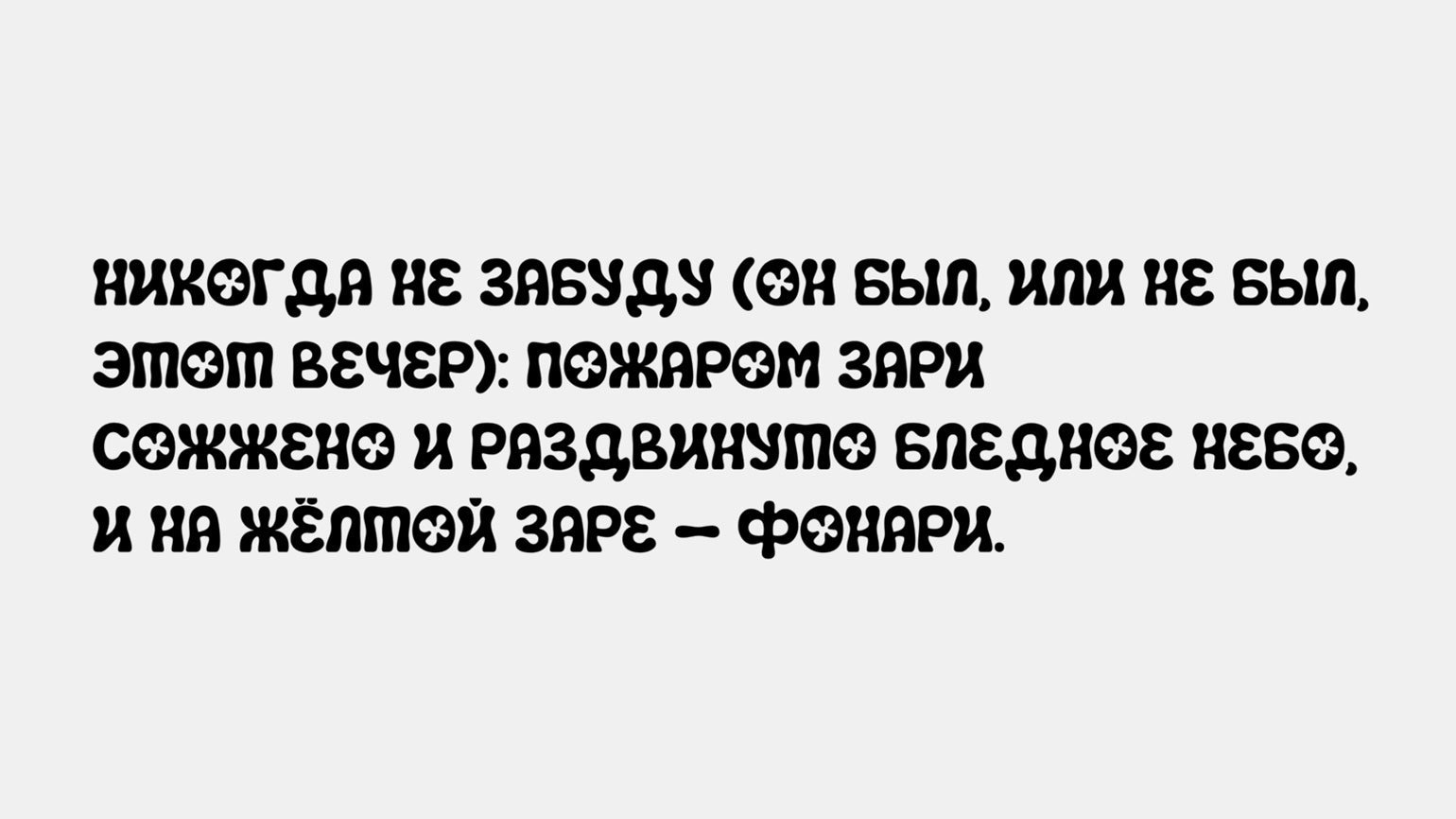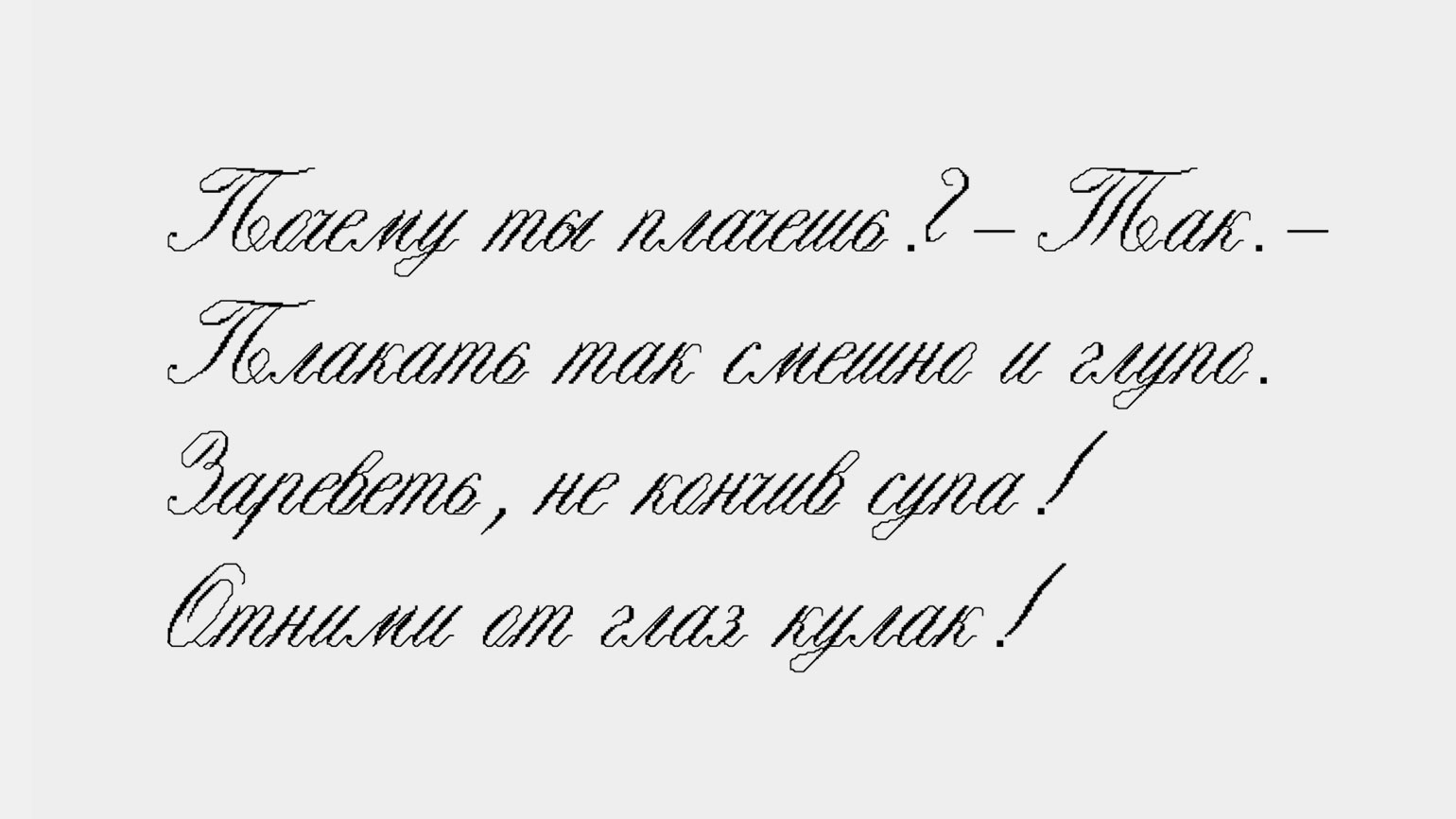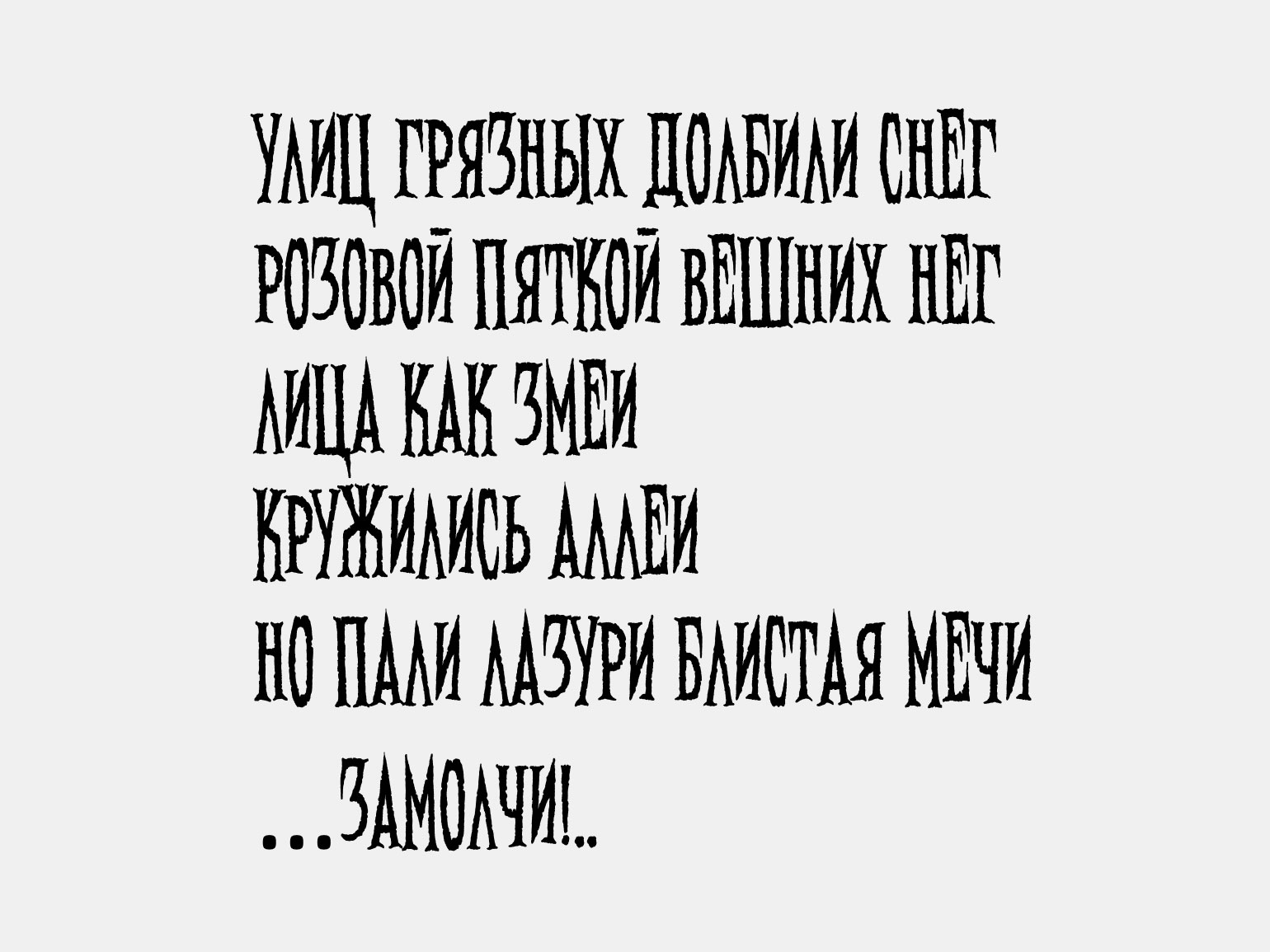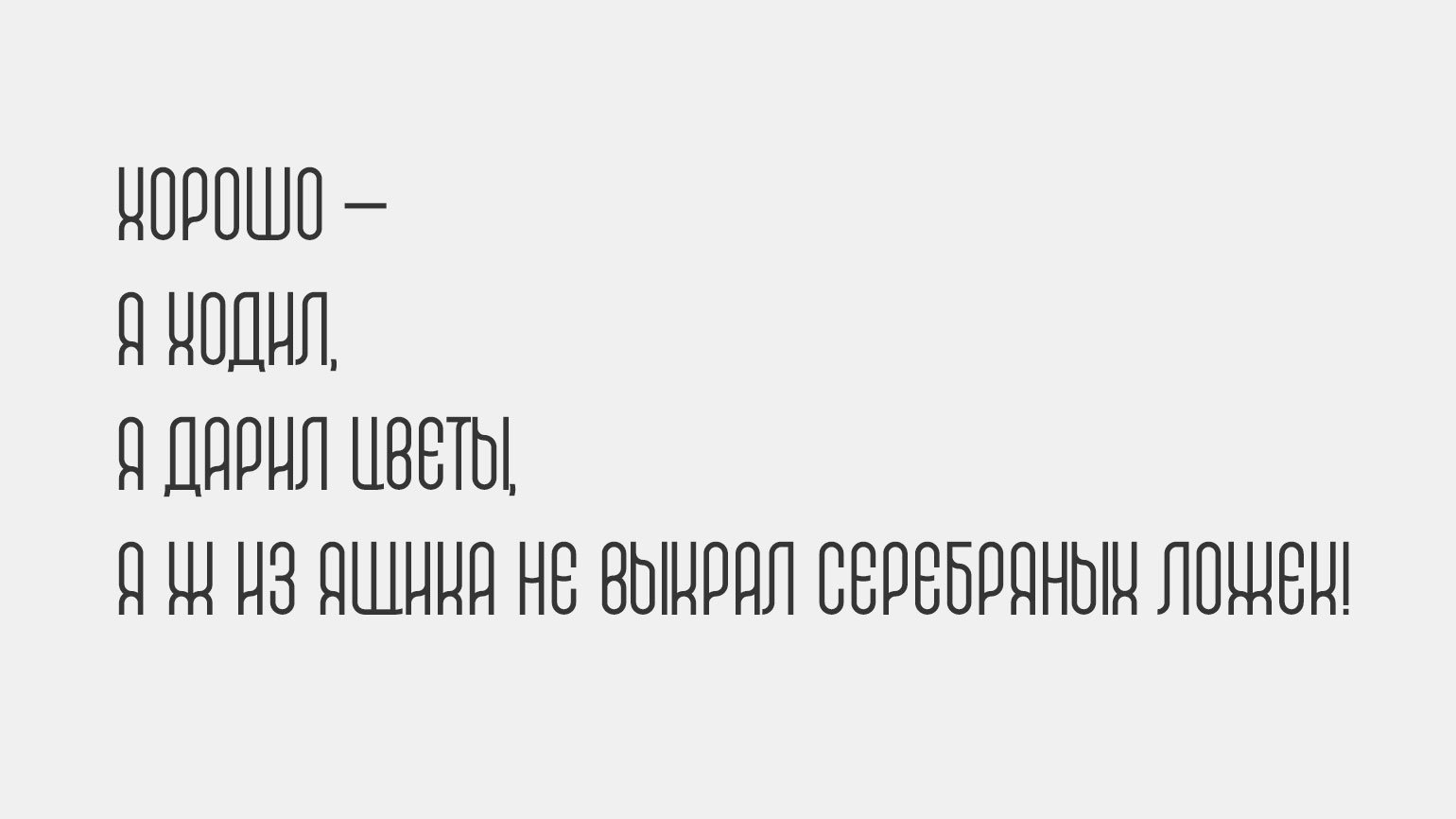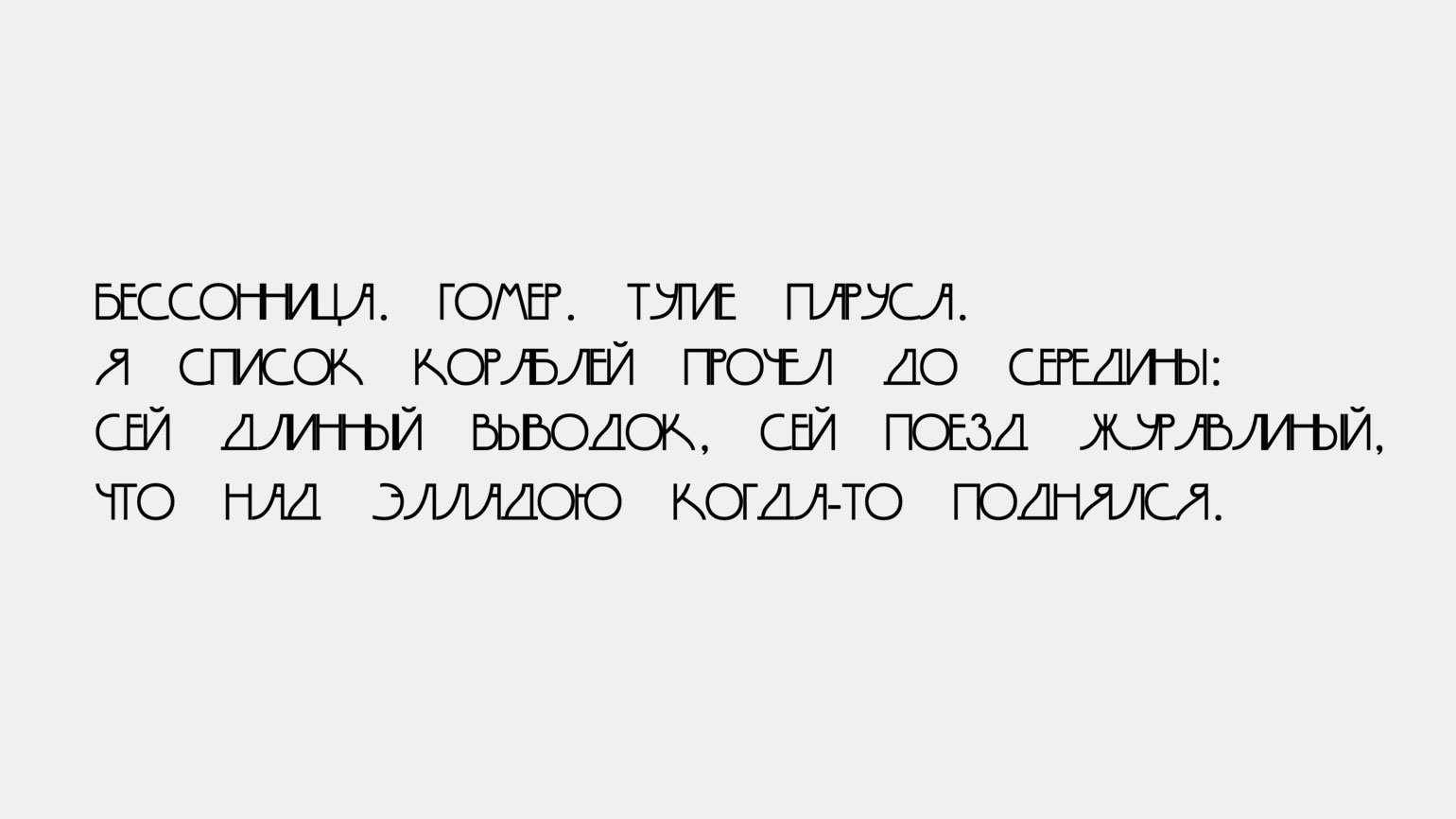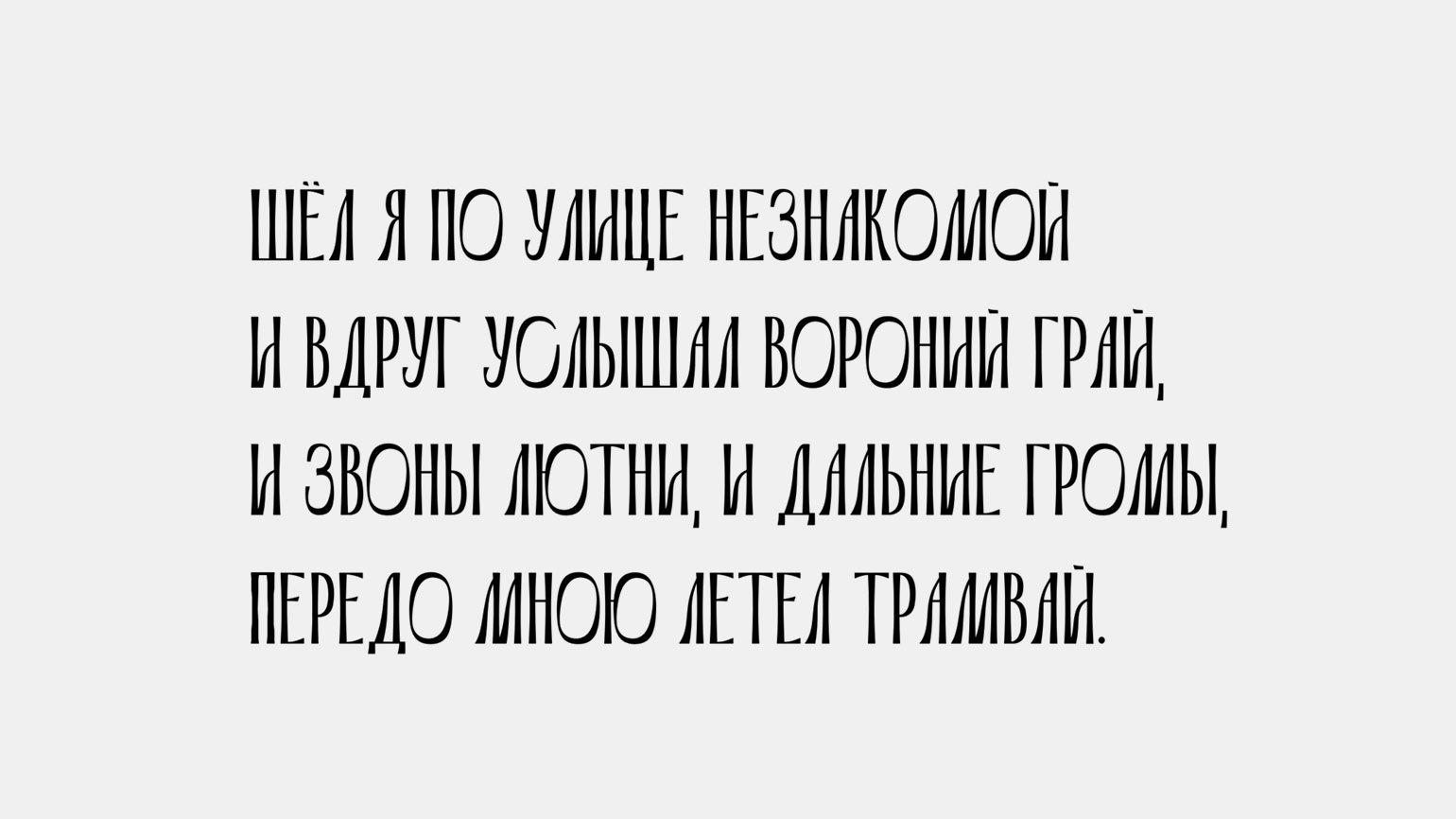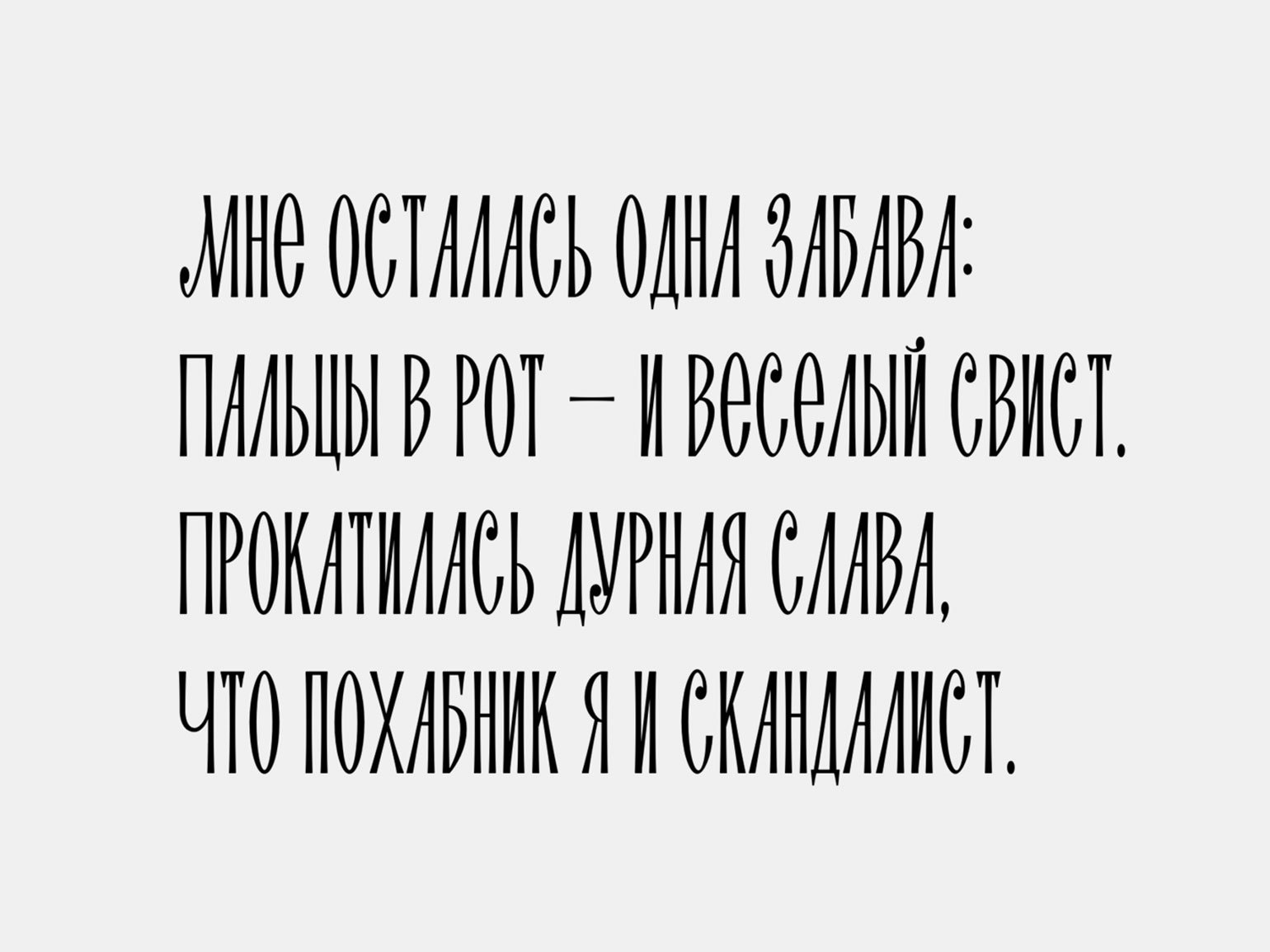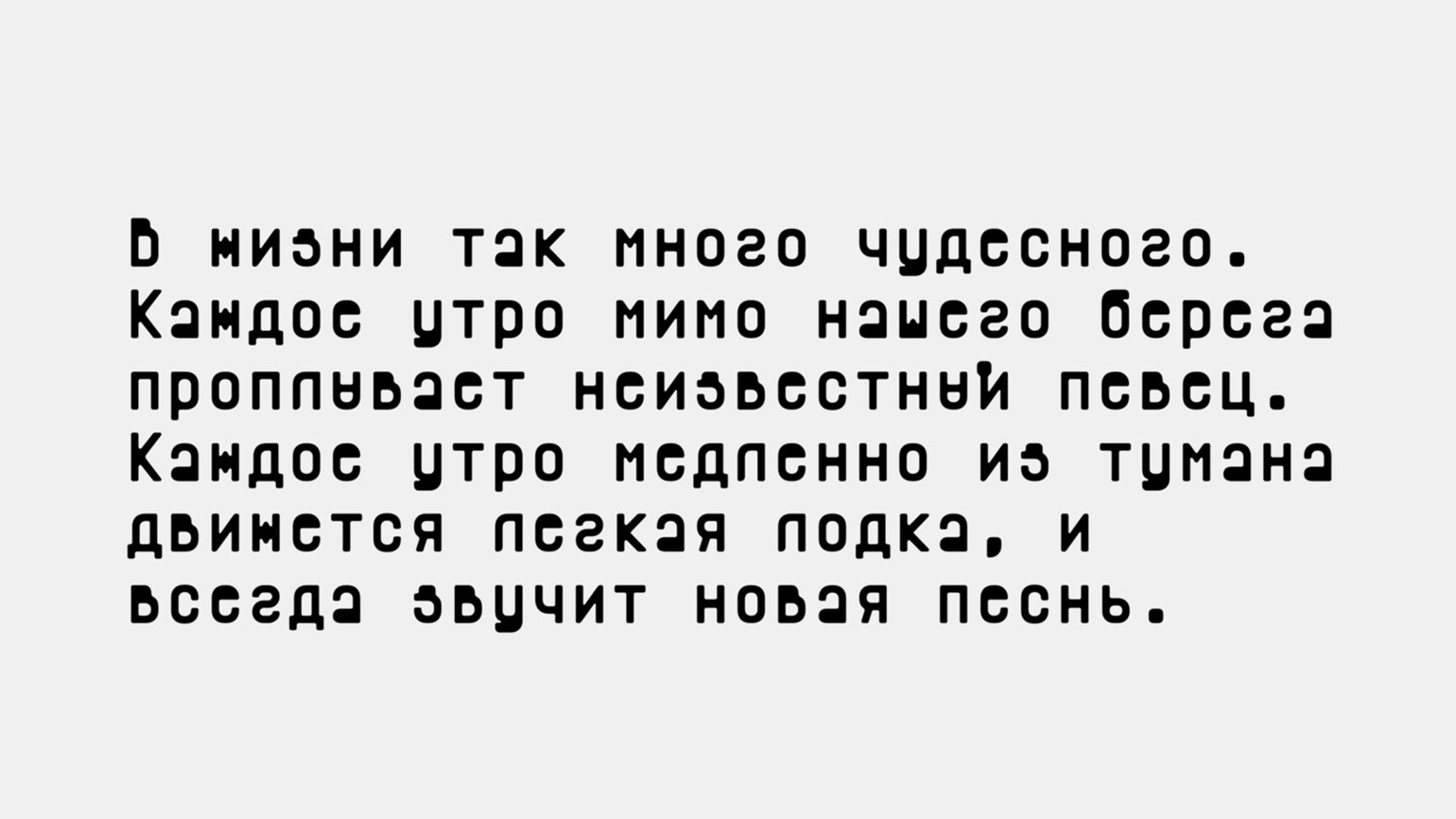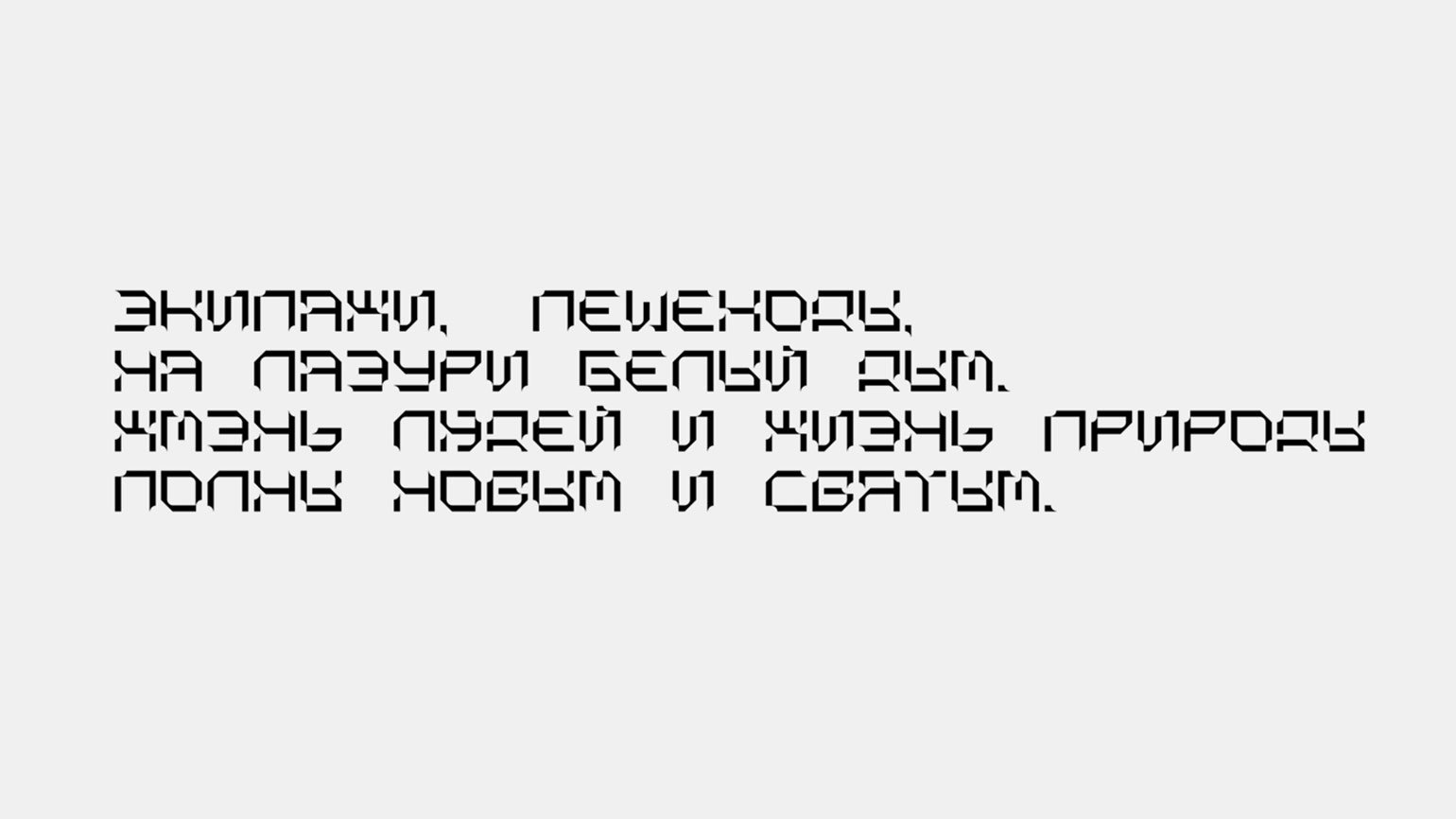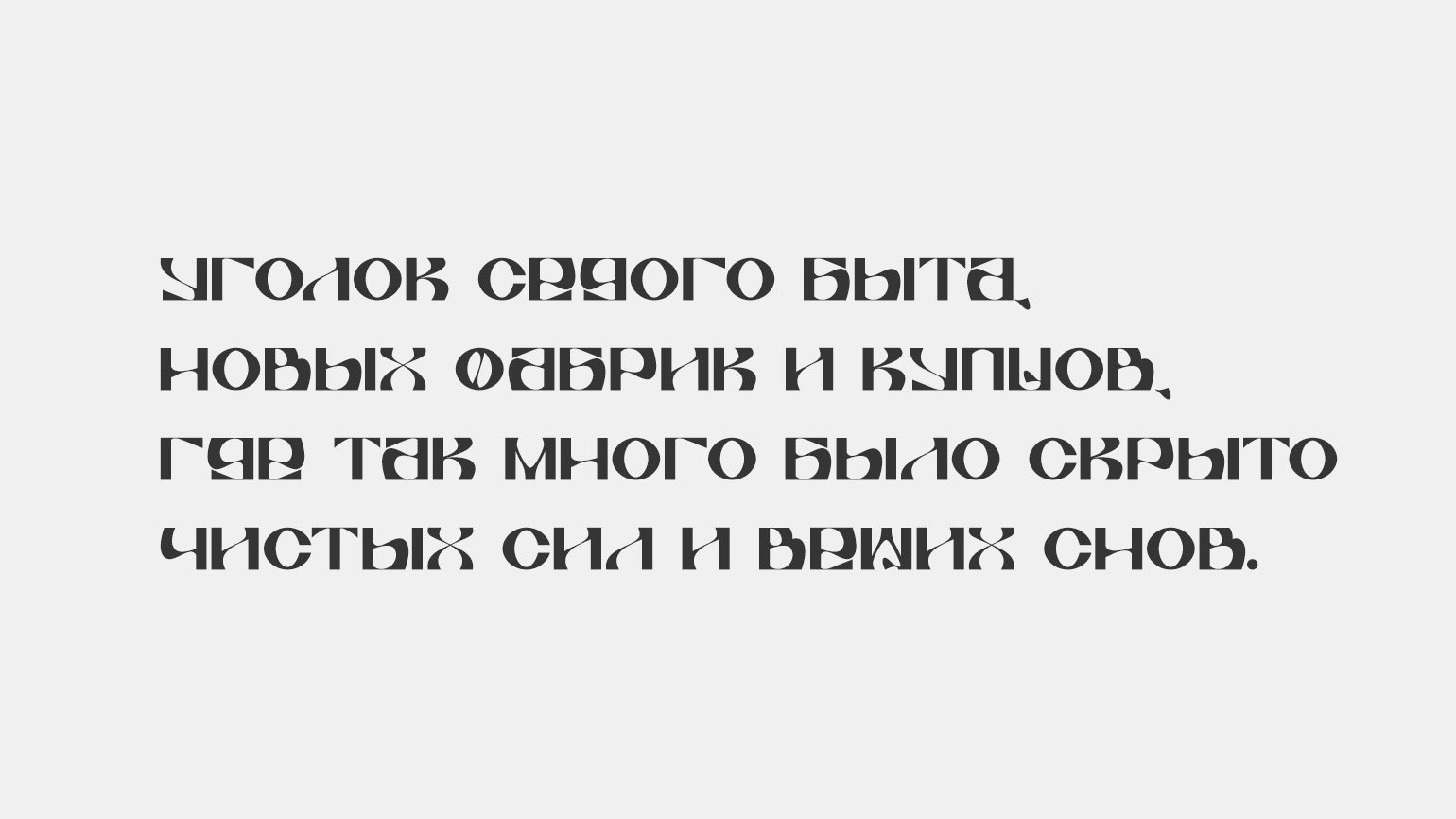
24 новых шрифта с кириллицей
Платные и бесплатные, декоративные и просто для текста: свежие шрифты с поддержкой русского языка для сайтов, логотипов и постеров.
Составили новую подборку гарнитур и начертаний с кириллицей:
• 16 красивых шрифтов для логотипов и заголовков на русском языке;
• 9 шрифтов без засечек, которые можно использовать для оформления текстов на лендингах, для айдентики и в печатных материалах.
Акцидентные шрифты с кириллицей
Lepka
Автор: Аня Трушина.
Стиль: декоративный шрифт, в котором буквы похожи на детскую аппликацию или наивные пластилиновые фигурки.
Состав: заглавные буквы латиницы, кириллицы, цифры и основные знаки препинания, а ещё сердечко.
Stezhok
Автор: Анастасия Фролова.
Стиль: пиксельный шрифт на основе прописей XIX века с контуром, как стежки в вышивке.
Состав: заглавные и строчные знаки кириллицы, цифры, кавычки и основные знаки препинания.
Needleteeth
Автор: Саша Павленко.
Стиль: декоративный шрифт в эстетике Halloween и «Семейки Аддамс».
Состав: заглавные буквы кириллицы, цифры, несколько основных символов.
Urban Slavic
Автор: Ольга Кондакова.
Стиль: новое прочтение русской средневековой архитектуры.
Состав: заглавные буквы кириллицы и латиницы, цифры, основные символы.
SC Portugal
Автор: Станислав Чиганов.
Стиль: акцидентный неконтрастный гротеск с плавными изогнутыми линиями, которые напоминают о лиссабонском модерне.
Состав: кириллица и латиница одного регистра, цифры, основные символы.
Riviera
Автор: Полина Солдатова.
Стиль: контрастный акцентный шрифт с танцующей пластикой, которая напоминает о лете и гедонизме.
Состав: кириллица и латиница одного регистра, цифры, основные символы.
Connector
Автор: Игорь Степанченко.
Стиль: моноширинный шрифт с характером рукописного, где буквы связаны линиями и есть следы пера.
Состав: расширенные кассы латиницы и кириллицы, цифры и большой набор специальных символов.
ST Brigantina
Автор: Александр Шиманов.
Стиль: шрифт посвящён детскому писателю Владиславу Крапивину и художественному наследию, которое оставили его книги о приключениях.
Состав: расширенная латиница и кириллица, касса которых поддерживает больше 15 языков.
Shreder
Автор: Виктор Кмит.
Стиль: экспериментальный модульный шрифт с «выпавшими пикселями».
Состав: базовые кириллица и латиница, цифры и основные символы.
Rublev
Автор: Даниил Видмич.
Стиль: «резной» акцидентный шрифт с отсылками к иконописи.
Состав: только кириллица.
LPM PuffPuff (aka Shutters)
Автор: Родион Илюхин.
Стиль: модульный шрифт с вариативной толщиной штриха. Его можно тянуть по ширине и деформировать.
Состав: базовая кириллица, латиница, цифры и основные знаки.
Milorad
Автор: Виктор Пушкарёв.